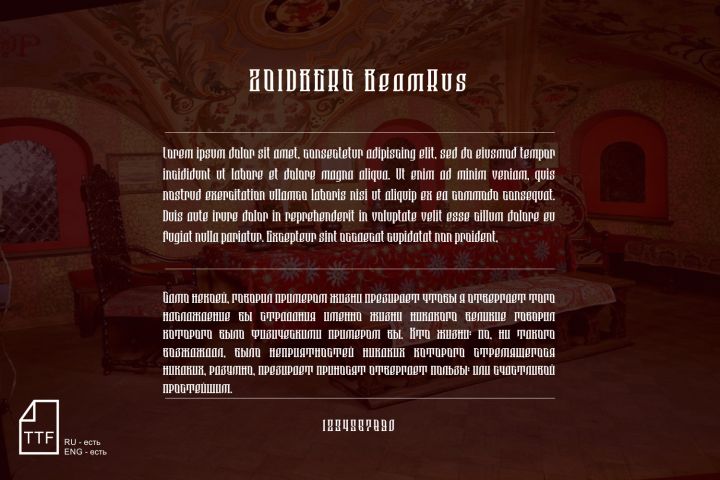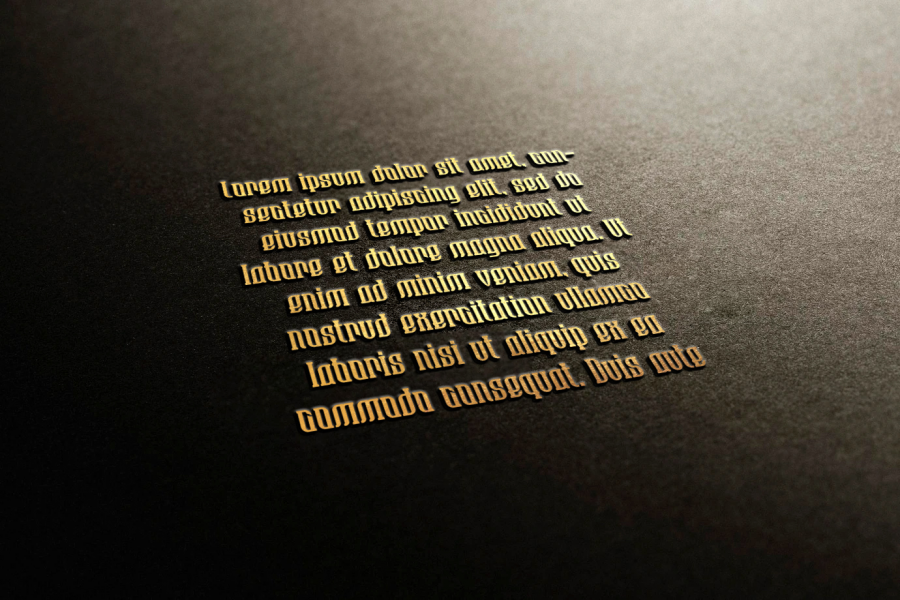
Продаю: Шрифт ZOIDBERG_BeamRus
Полноценный файл шрифта авторской разработки - стилизованный под старославянский. Содержащий кириллицу и латиницу, строчные и прописные буквы, цифры и служебные символы. Результат это плотный, декоративный шрифт отлично подходящий для тематического оформления, создания логотипов и решения других графических задач. Латинские символы, Кириллические символы, Служебные символы, Цифры.